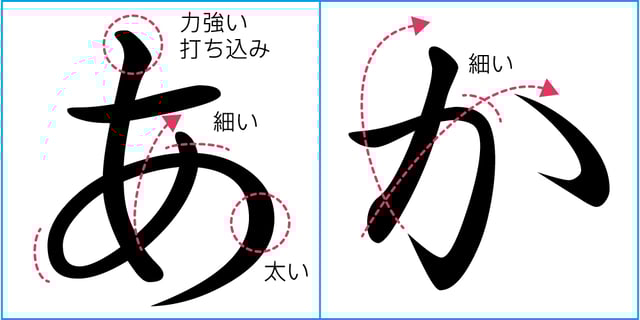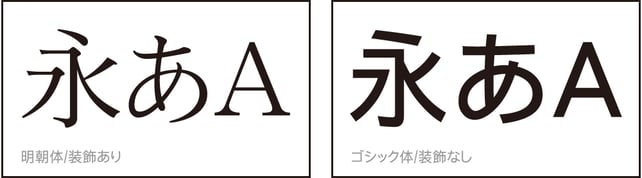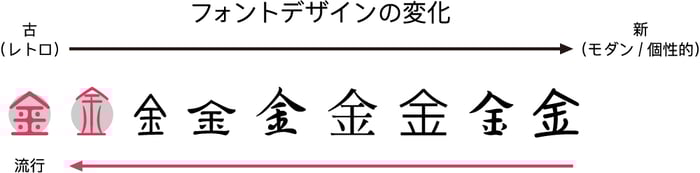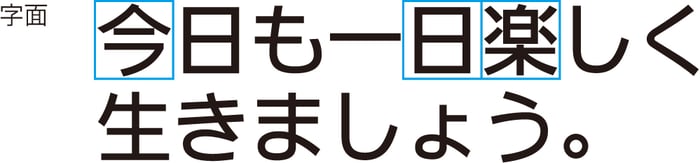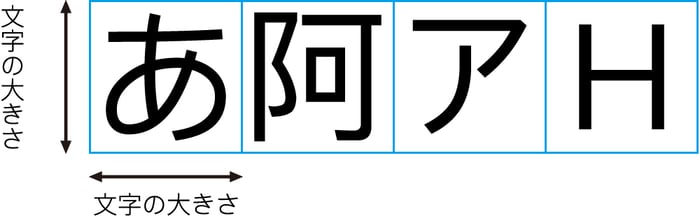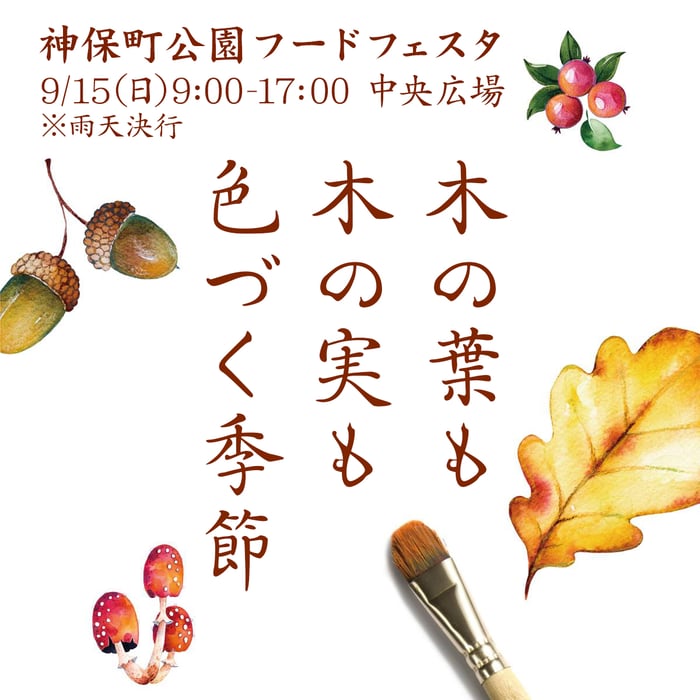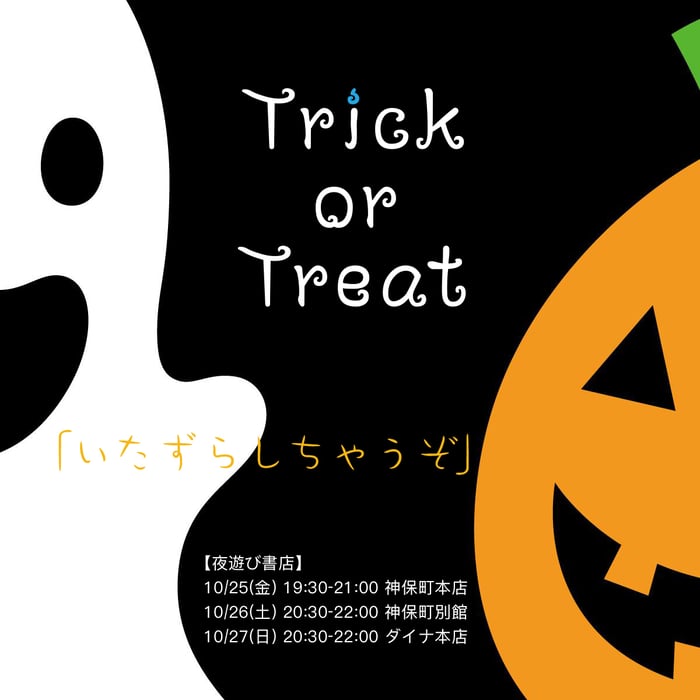
フォント選びに迷った時に。フォントデザイナーが教える日本語フォントのトレンド・使い方
身近なものではチラシやポスター、SNSやブログのアイキャッチ、ホームページなど、皆さんが普段目にしているデザインには、様々なフォントが使われています。デザインを作成するうえで、印象を左右するフォント選びはとても重要です。フォントの特徴や扱い方を知っているだけで、デザインの仕上がりは大きく変わります。
今回の記事ではフォントデザイナー目線で、ノンデザイナーの方でも理解しやすいよう、フォントの特徴からデザインに使用する際のコツまで、フォントの魅力をお伝えします。
「日本語フォント」と「欧文フォント」の違い
日本語フォントは「ひらがな」「カタカナ」「漢字」の組み合わせで出来ており、構造が複雑です。そのため、デザインする際は、ひらがな、カタカナ、漢字それぞれのスタイルに一貫性を持たせてデザインをしなければなりません。統一感がありバランスが取れた状態でないと、良い日本語フォントとはみなされないからです。
また、「縦長」「扁平」「方形」「円形」といったさまざまな形状の文字がありますが、全ての文字を正方形の枠の中に収めることで横組みと縦組みの長さを均等にしています。
また、日本語のかな(ひらがな)は、筆遣いに強弱がつくことで線の太さに変化が生まれ、書のように文字のリズム感を表現することが出来るという特徴があります。しかし、デジタルデバイスに合わせて開発された、シンプルで洗練されたモダンなゴシック体に関しては例外です。
それに比べて欧文フォントは、決まったアルファベットのみの組み合わせで出来ているので、日本語フォントと比べると構造は単純です。しかし、大文字、小文字の基準線の高さが異なり、左右の幅も文字ごとに異なっています。
欧文フォントをデザインする際は5つの基準線に合わせていきますが、文字によってそれぞれ字間は異なります。アルファベットは上下に線が伸びることがあり、小文字の「j」や「y」はディセンダー(ベースラインの下に延長した部分)まで線が伸びています。
デザインにおけるトレンドフォントの移り変わり
フォントの流行りには、大まかな傾向があります。当初、デザイン業界では基本書体(明朝体、ゴシック体、楷書体、丸ゴシックなど)が主流でした。その後、個性的な書体がデザインに取り入れられるようになり、フォント業界も数々の個性的な書体を開発するようになりました。近年では、古代文字をデジタル化したフォント(金文、篆書、甲骨文など)が流行の兆しを見せていることから、デザイン業界でも「レトロ」がブームとなっています。
最近、タイトルに使われることが多いのがレトロな書体です。金文体と、金文と甲骨文を掛け合わせた「甲金文体」は、中国先秦時代の古代文字から発想を得てデザインしたもので、現代人でも分かりやすいようにリファインされたデジタルフォントです。看板やパッケージのタイトルとして使われることも多く、他のフォントベンダーも古代文字にインスパイアされた書体を次々とリリースしています。昔の文字に対する興味だけではなく、古代文字には象形化という特徴があるので、現代で言うところの絵文字や顔文字が流行を後押ししているのかもしれません。
また、本文に使用するのは、読みやすいゴシック体が人気です。ゴシック体の場合、DTP(パソコンでデータを作成し、実際に印刷物を作成すること)用に開発された書体と、現在流行しているゴシック体は全く別ものです。
伝統的なゴシック体はふところが狭く、起筆には打ち込みと呼ばれるラッパ形のアクセントが付いています。それに対して現代のゴシック体はデジタル時代に対応し、ディスプレイや電子書籍など(特に小型液晶)でもはっきりと読めるよう、ふところがやや広めにデザインされ、直線的ですっきりとしたストロークがトレンドとなっています。
▶︎使用書体:平成ゴシック体
ふところ(ピンクの部分)が狭く、起筆にアクセントが付いたゴシック体はDTP向けに開発された書体です。ふところを狭めた書体は伝統的なイメージになります。
▶︎使用書体:UDゴシック体
広めに取られたふところと、直線的ですっきりとした現代版ゴシックです。
また、昨今ではパソコンやスマートフォンなどが普及したことにより、はっきりと読みやすいだけではなく、下記のようにファミリー展開(同じデザインの書体で太さを変えて作られたひとまとまりのグループ)されている書体や、多言語に対応した書体もブームとなっています。
こちらの「金剛黒体」は6種のウェイトと15言語で展開されており(100ヶ国近い国や地域の言語をカバー)、ネットワークのグローバル化、ボーダレス化の時代におけるトレンドに訴求した書体となっています。
グラフィックデザインにおける日本語フォントの組み合わせ
フォントを組み合わせる際は、全体のスタイルと雰囲気を考えることが大切です。例えば、信頼感を前面に出したいデザインには、子供っぽいフォントは適しません。また、1つのデザインで3書体を超えて使用するとデザインにまとまりがなくなり、焦点がずれてしまうので書体数は絞ったほうが効率的です。
フォントの組み合わせ事例
【例1】
▶︎使用書体:(タイトル)華康楷書体W5、(サブタイトル)金剛黒体Semibold、(本文)金剛黒体Light
タイトルに楷書を使用し、基本書体であるゴシック体や明朝体を合わせることで誠実な印象を与えられます。 タイトルをミディアムウェイト(大)、サブタイトルを太いウェイト(小)、本文を細いウェイト(極小)という順番で並べることで、はっきりと階層を作ることができます。
【例2】
▶︎使用書体:金文体→金剛黒体Thin→華康明朝体
細めの書体をタイトルに使用し、基本書体であるゴシック体や明朝体を合わせることで、優雅で奥ゆかしい雰囲気を表現することができます。タイトルとしては文字が細く感じるかもしれませんが、サイズを大きくすることでインパクトを与え、目を引くような効果を作り出すことができます。
タイトルを細いウェイト(大)、サブタイトルを細いウェイト(中)、本文を細いウェイト(小)という順番で並べることで階層をはっきりと分けることができます。
フォントを選ぶことは、スタイリストがクローゼットの中にある洋服を組み合わせてコーディネートを作り出すようなものです。フォントを選ぶことと、どのようなスタイルや雰囲気にしたいのかということは関連性があります。
デザインに活かせるフォント選びのコツ
一般的にグラフィックデザインにおけるフォントには、大きく「タイトル(見出し)」「サブタイトル」「本文」という3つの階層があります。フォントの組み合わせと階層のレイアウト、全体の雰囲気は大きく関係しています。
また、フォントそれぞれの特徴を把握することで、デザインのクオリティ向上にも繋がり、階層はフォントの大きさやウェイト(線の太さ)の変化で緩急を付けることができますし、文字の大きさや太さを使い分けることで、一味違ったデザインになります。
タイトル(見出し)
訴求したい内容を目立たせ、人々の目を引かせる必要があります。ゴシック体の他にも楷書体(かいしょたい)などの基本書体から、全体の雰囲気に合うようなデザイン書体も選択肢に挙げられます。
サブタイトル
タイトルより目立たせないよう、タイトルの書体に近い雰囲気もしくは基本書体にしましょう。
本文
内容を伝えることが一番の目的なので、はっきりと読みやすいフォントを選ぶことがポイントです。基本書体の明朝体、ゴシック体もしくは丸ゴシック体などが適しています。
▶︎使用書体:タイトル「てがき魔」、サブタイトル「クラフト童」、本文「金剛黒体」
魔法をイメージさせながら、情報はよみやすく
ハロウィン向けのデザインなので、訴求したい内容と雰囲気に合わせて、タイトル部分は魔法をイメージさせるような「てがき魔」を使用しています。サブタイトルはタイトルに合わせてウェイトが細めのクラフト童を選び、ハロウィンの「いたずらっぽさ」を前面に押し出しています。日時や場所などの情報には、はっきりと読みやすいゴシック体を使用しています。
▶︎使用書体:タイトル「古籍糸柳」、サブタイトル・本文「華康楷書体」
近いスタイルの組み合わせで印象を強く
こちらのデザインでは、2書体を組み合わせています。タイトルには優雅で美しく、詩情豊かな「古籍糸柳」を使用し、サブタイトルはタイトルと近いスタイルの「華康楷書体」を合わせることで、古風で文学的な雰囲気を持たせています。
▶︎使用書体:タイトル「太丸ゴシック体」、サブタイトル「ナーティ」「中太丸ゴシック」、本文「金剛黒体」
親近感を持たせつつ、メッセージはしっかりと
これはある程度、決まりに則ってデザインされた例です。タイトルには動物愛護というテーマに相応しい、身近に感じることができるような丸ゴシック系列の書体を使用しています。
本文は読みやすくするため、ゴシック体を使用しています。また、サブタイトルに使用している「ナーティ」という書体は、遊び心がありながらもストロークがある程度整っているので、適度な塩梅でデザインに生き生きとした要素を与えることができます。可愛らしい動物が描かれていますが、動物愛護という真面目な内容なので、デザイン性が高すぎる書体は避けましょう。
注目されやすい、読んでもらいやすいフォントとは?
本来フォントの役割は、文章を読みやすくすること=「可読性」と、読者の目を引くために文字を目に留まりやすくすること=「視認性」です。フォントの特製を理解し、適切に使用することで、読者や消費者の行動に影響を与えることが出来ます。
例えば「明朝体」は、一般的に線の太さに変化があるので、長文でもストレスを感じることなく読み進めることができ、うろこと呼ばれる三角形の装飾が右方向に向かって視線を誘導してくれるので読みやすい書体です。
それに比べて「ゴシック」体は線の太さの変化が少なく、装飾もないので(伝統的なDTP向けの書体はゴシック体でも多少の装飾はあります)、目を引くような効果をもたらすことができます。欧文フォントに関しても、装飾のあるフォント(セリフ)は本文に適しており、装飾のないフォント(サンセリフ)はタイトルや見出しに適した書体といえます。
また、字面の大きさに合わせて行間を調整することで、文章を読みやすくしたり、文字を目立たせることができます。
字面が大きく行間が広いほど「視認性」が高いため、注目してしてもらいたいときにおすすめです。また、字面が小さめで適切な字間にするほど「可読性」が高くなります。しかし、日本語の場合は日本語の組版(原稿やレイアウトに合わせて文字や図版を配置すること)で文字幅を調整しないとアキが目立ち、文章が読みにくくなってしまう場合があります。
時代の流れと共に移り変わっていくフォント
昔はバリエーションが少なく、フォントは単に情報を伝えるためだけのものでした。現在ではフォントが多様化したことで、デザイナーも監督が出演する俳優を選ぶようにデザインに合ったフォントを選び、個性を表現できる時代になりました。フォントの種類が多くなるほど、それに合わせて様々な個性を表現することが可能です。私たちフォントデザイナーは、日常生活の衣、食、住、交通、教育、エンターテイメントにおける、美味しさ、クオリティ、信頼感、スピード感、安心感、リラックス、楽しさといった要素まで、フォントで表現できるようになっています。